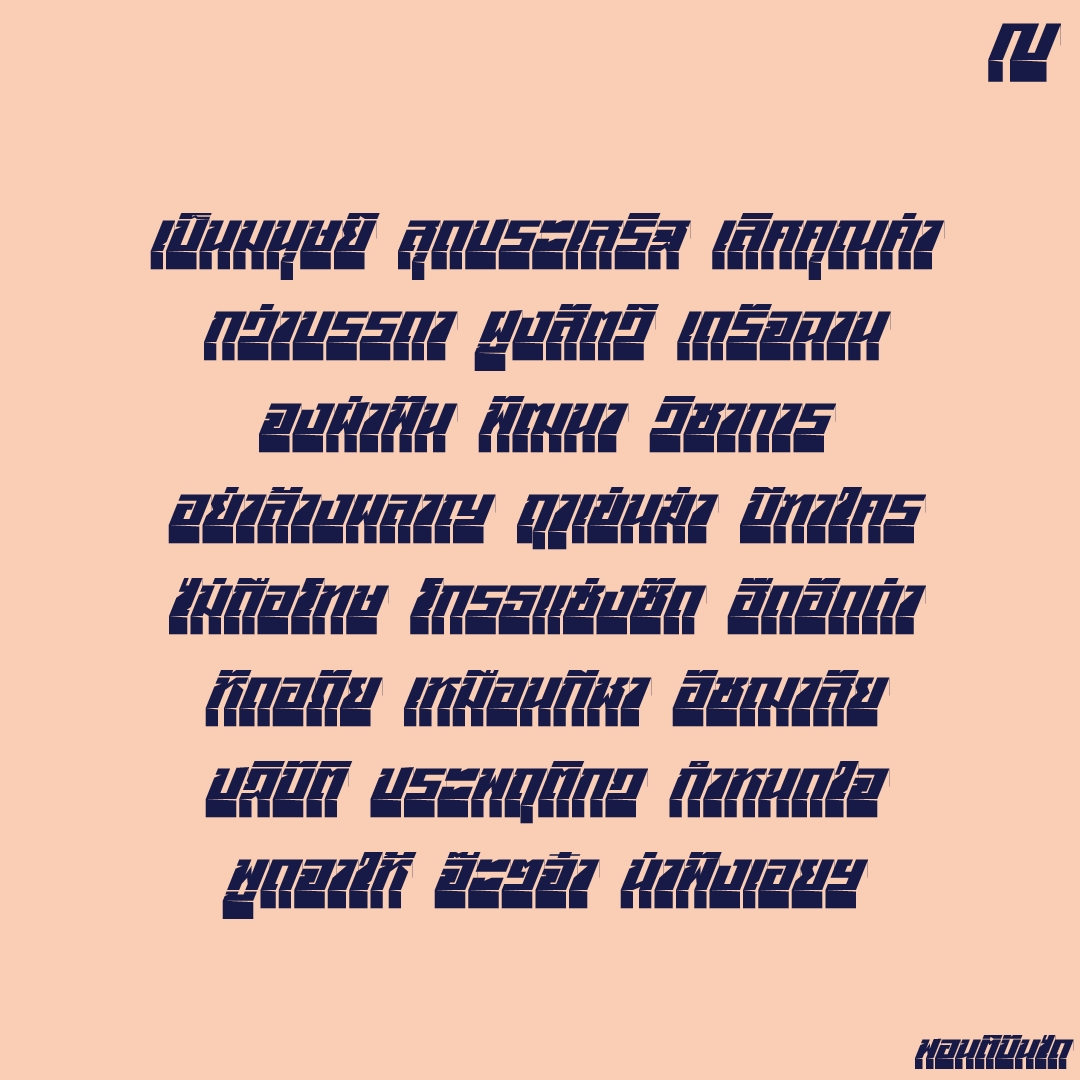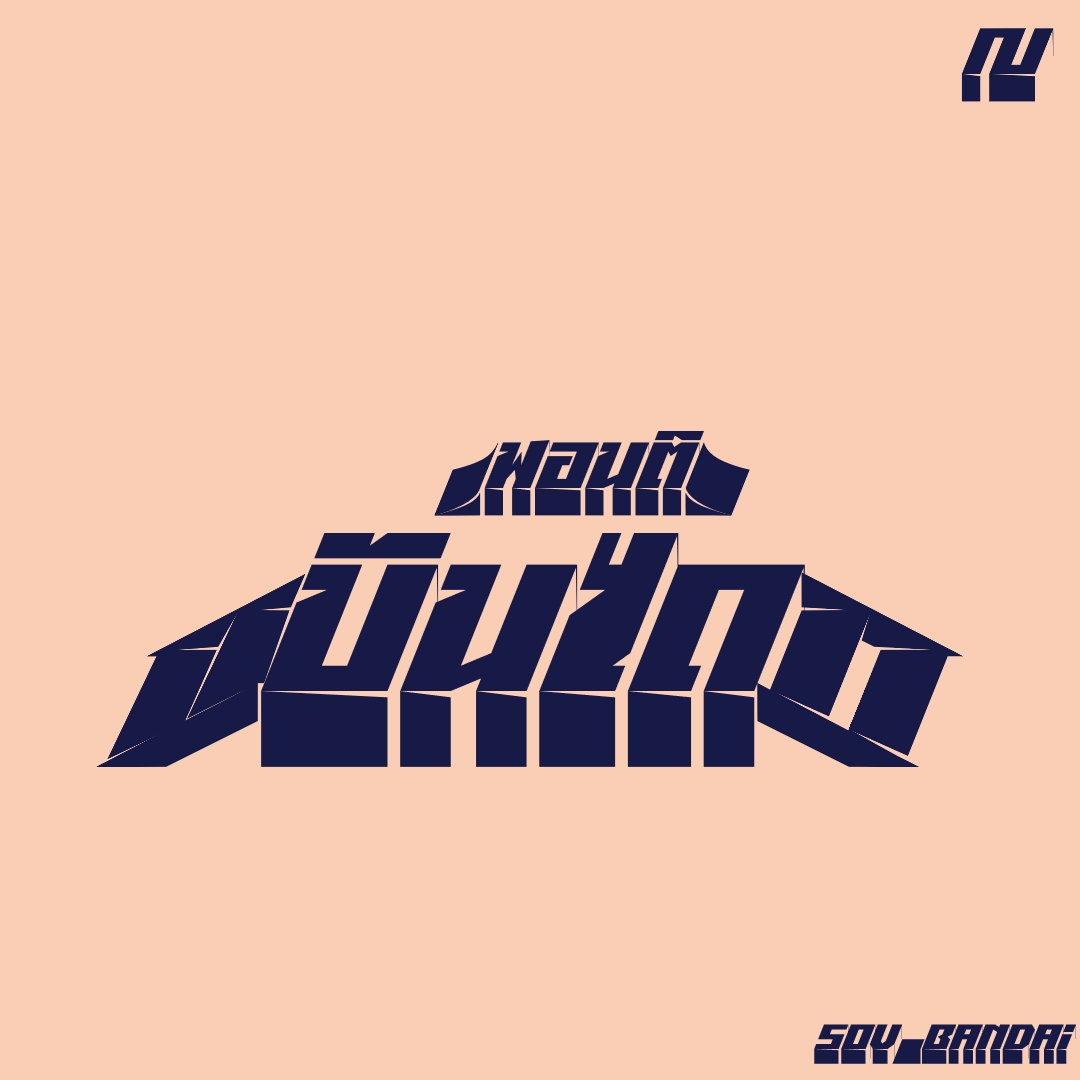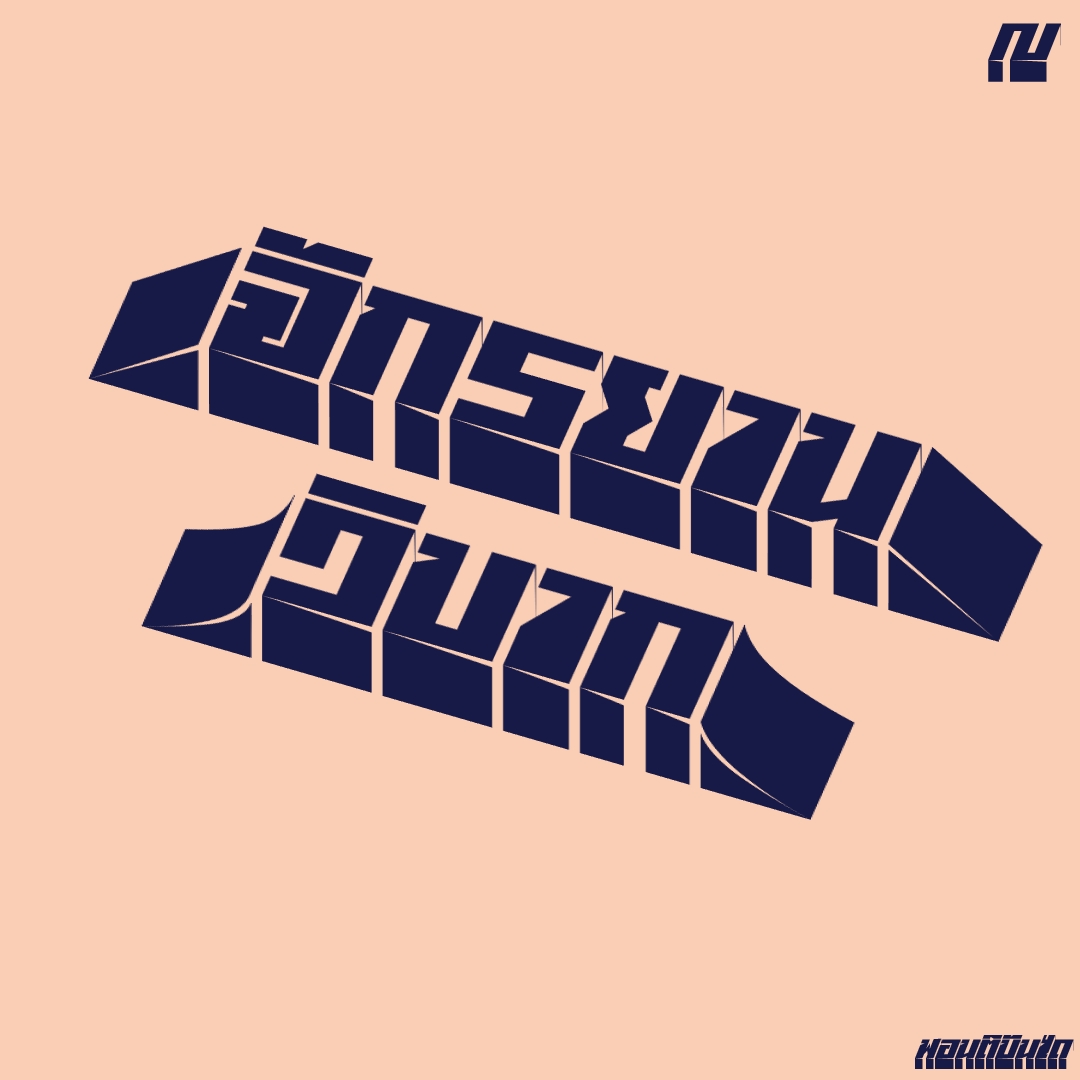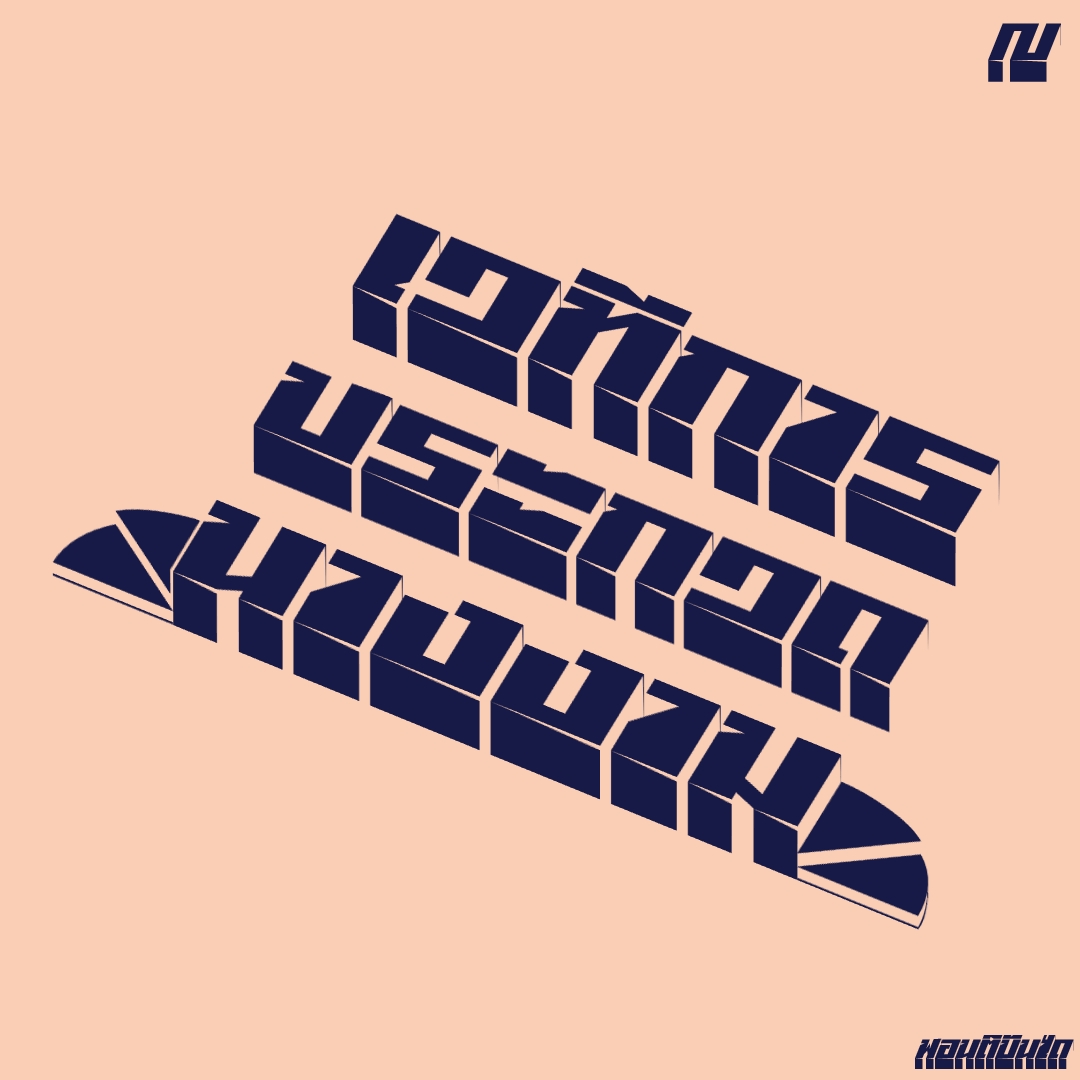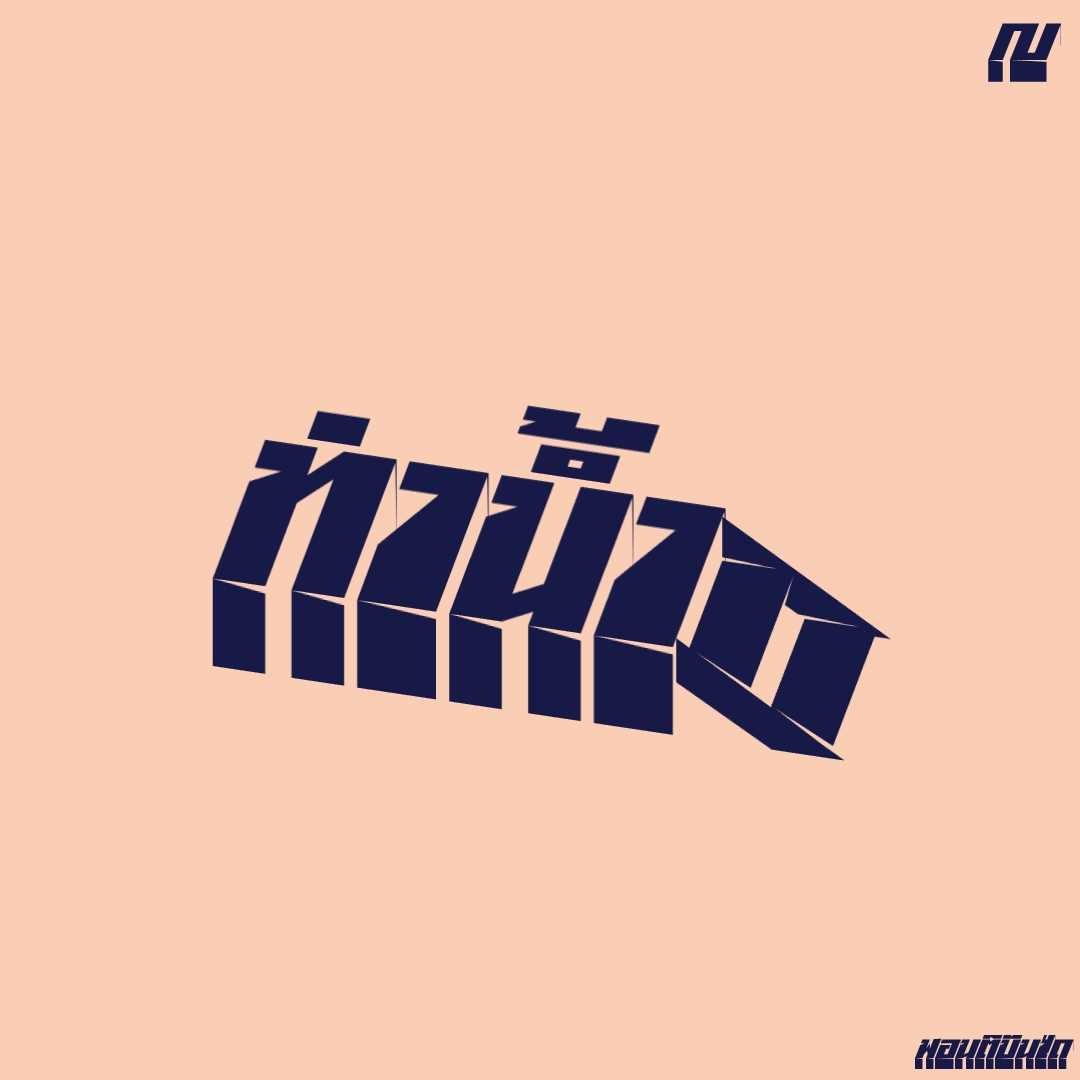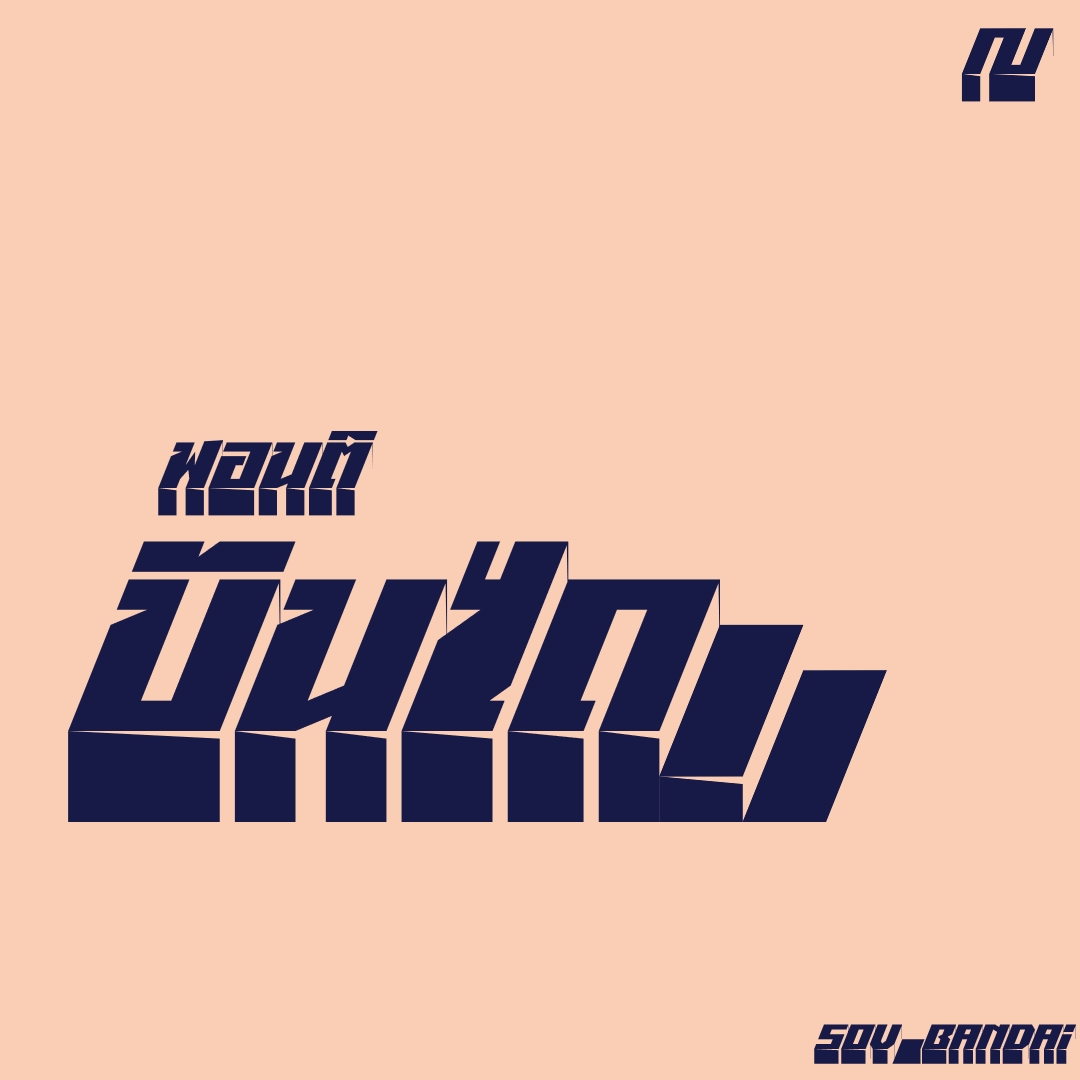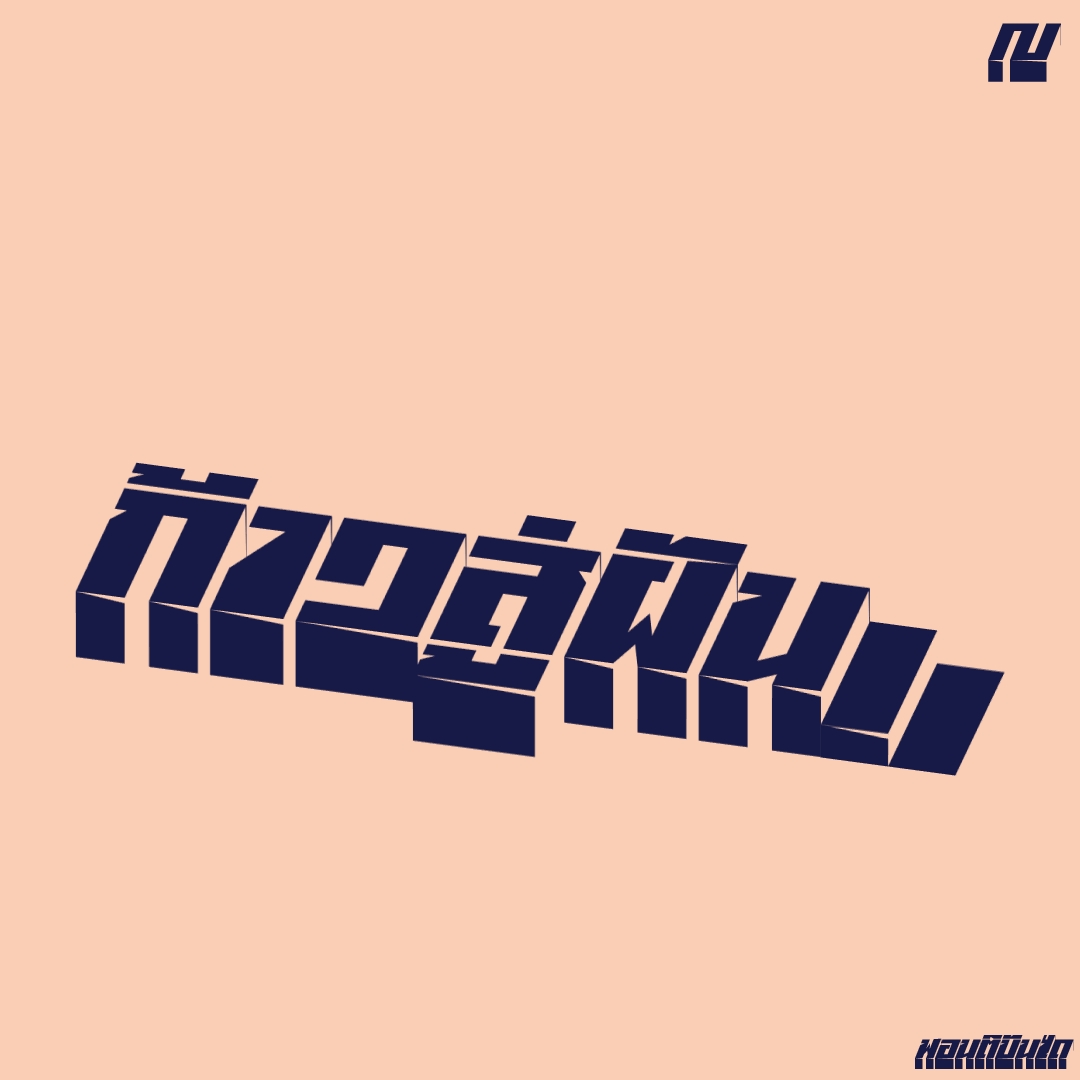
ฟอนต์ บันได :
ฟอนต์แนวราบ ยกพื้น เป็น 3 มิติ มีบันไดให้ขึ้น ทั้งซ้ายขวา ..พิมพ์วงเล็บ จะได้บันได
ชื่อฟอนต์ : บันได
ฟอนต์แนวราบ ยกพื้น เป็น 3 มิติ มีบันไดให้ขึ้น ทั้งซ้ายขวา ..พิมพ์วงเล็บ จะได้บันได